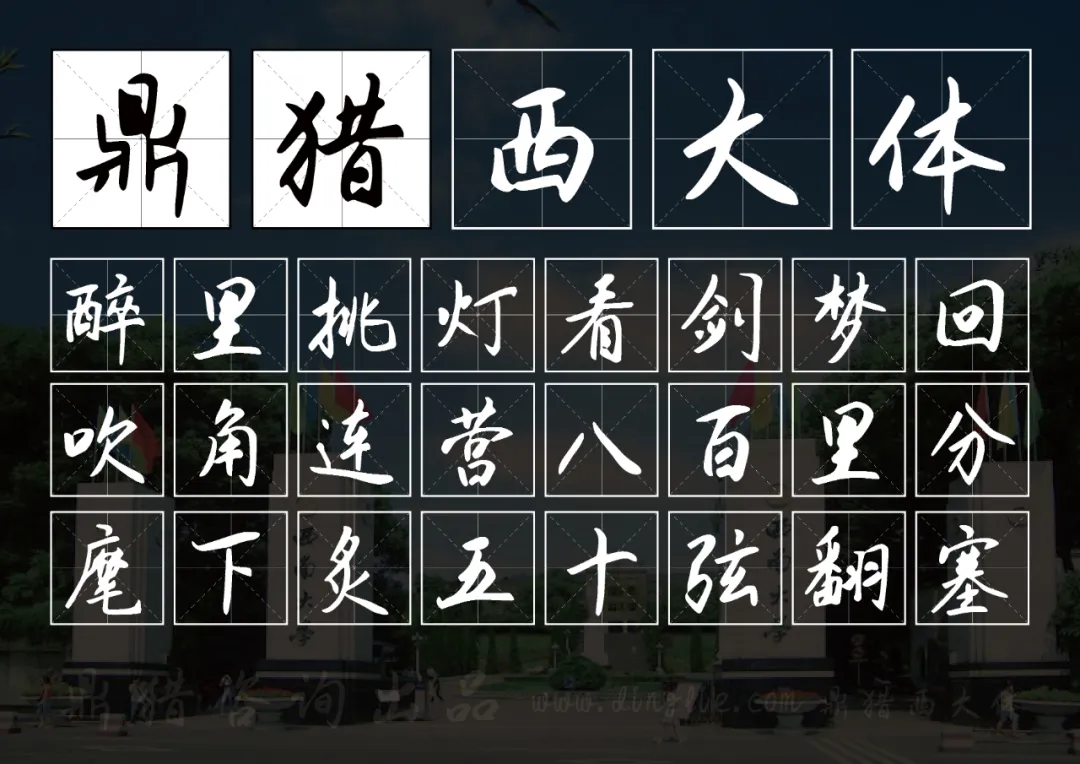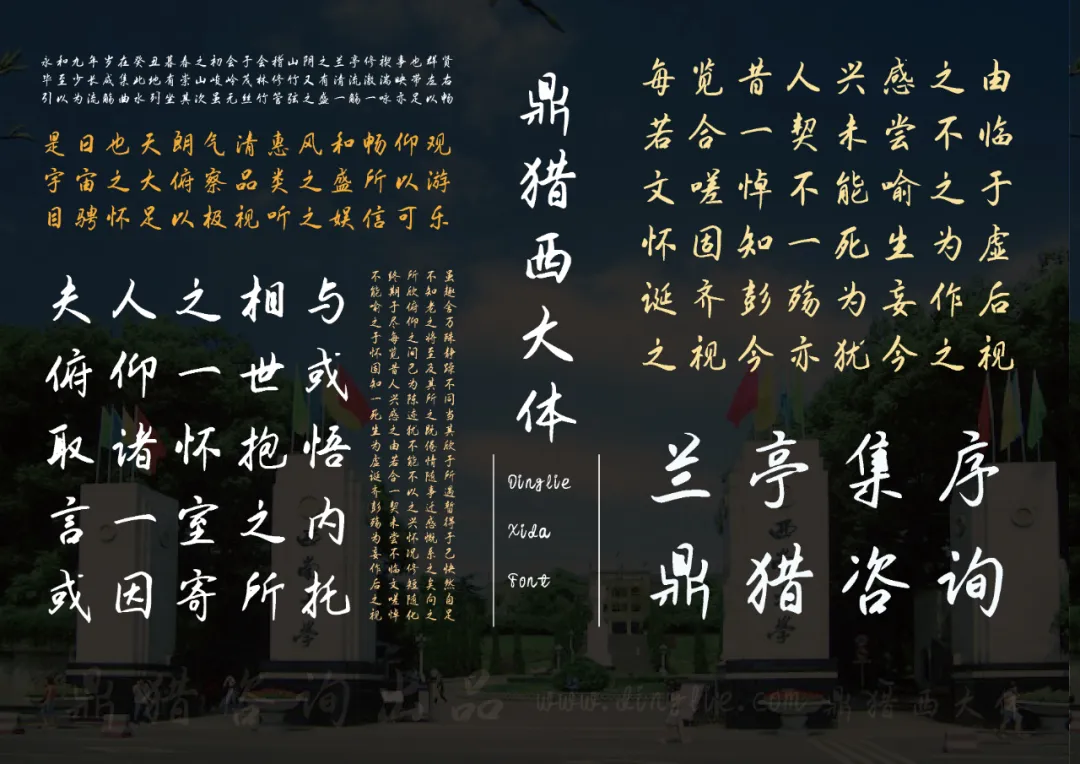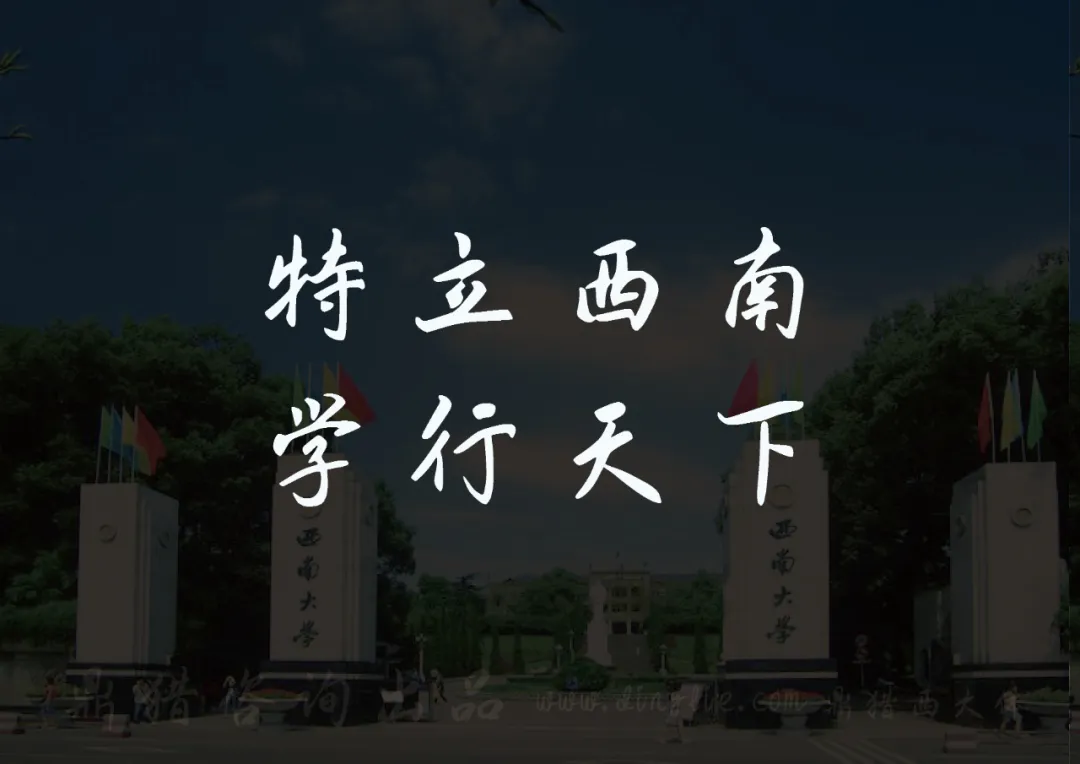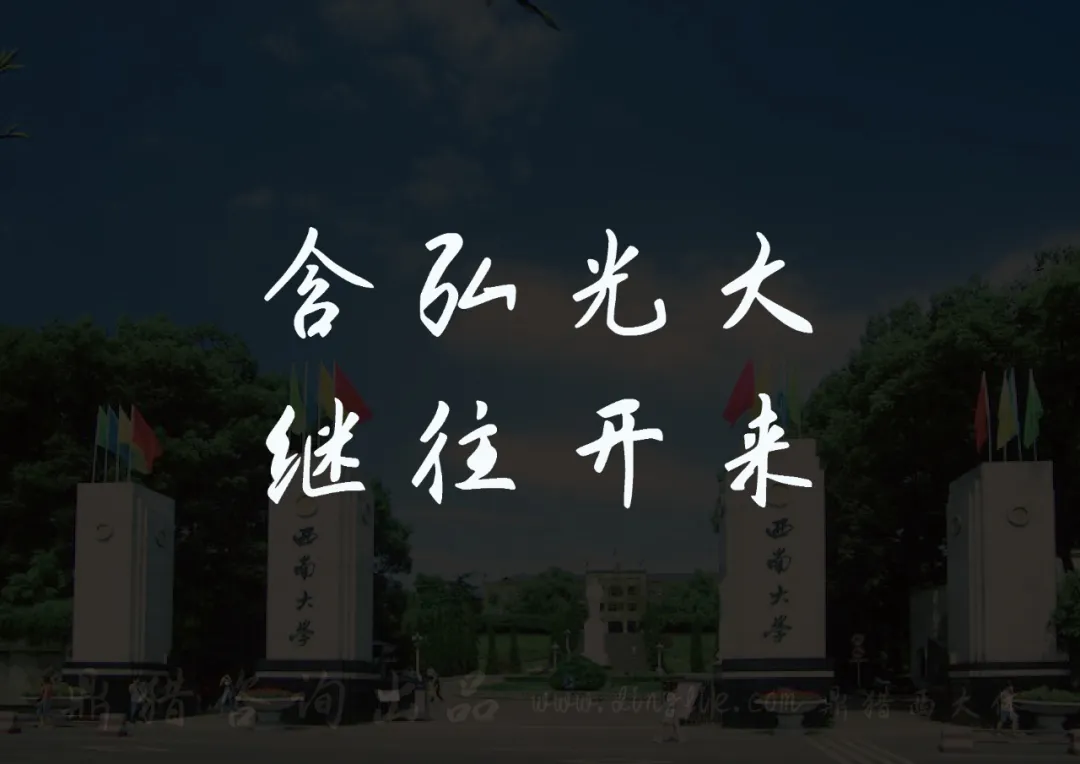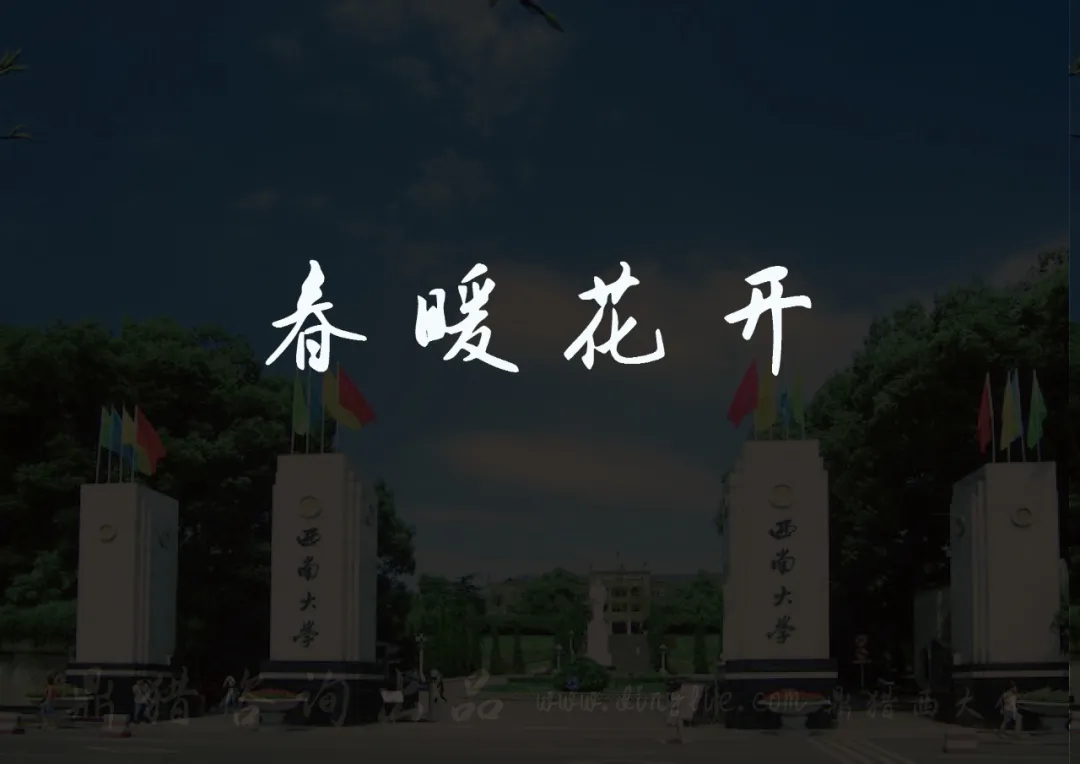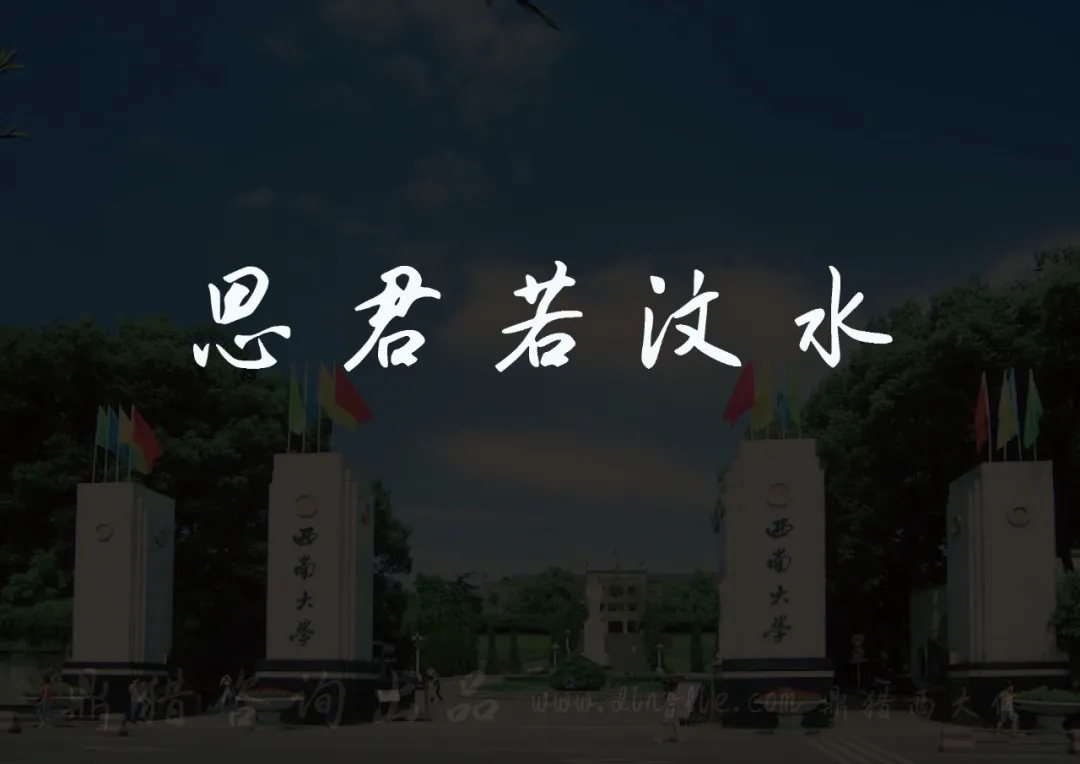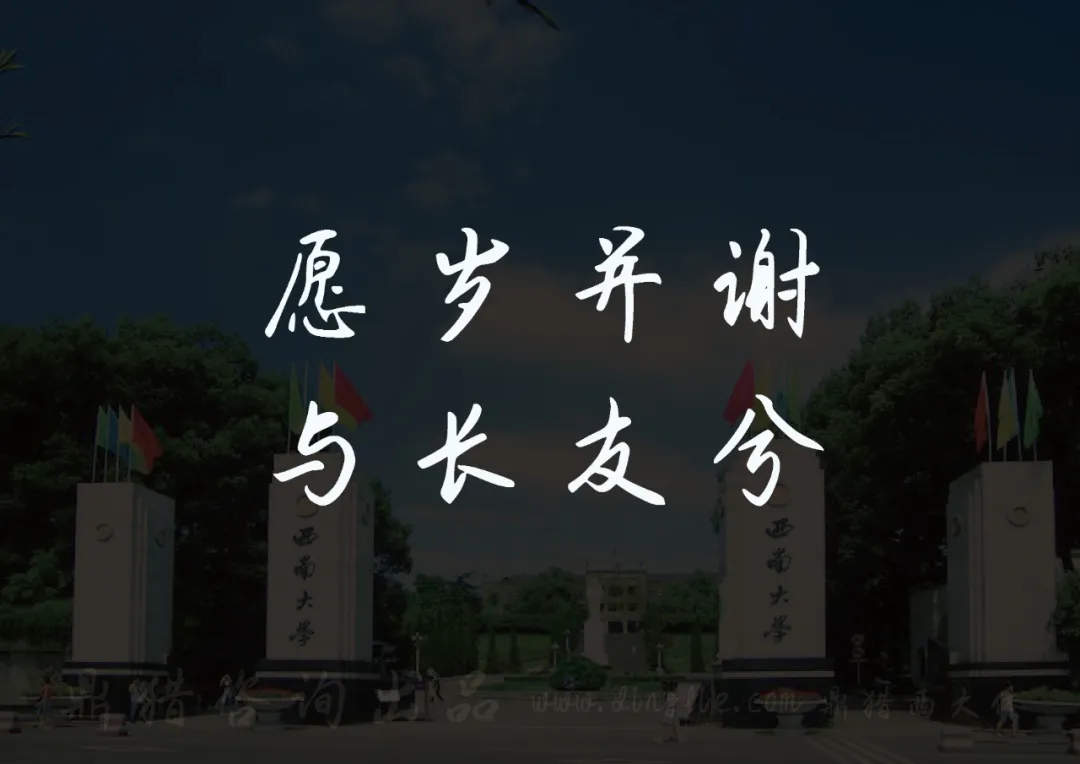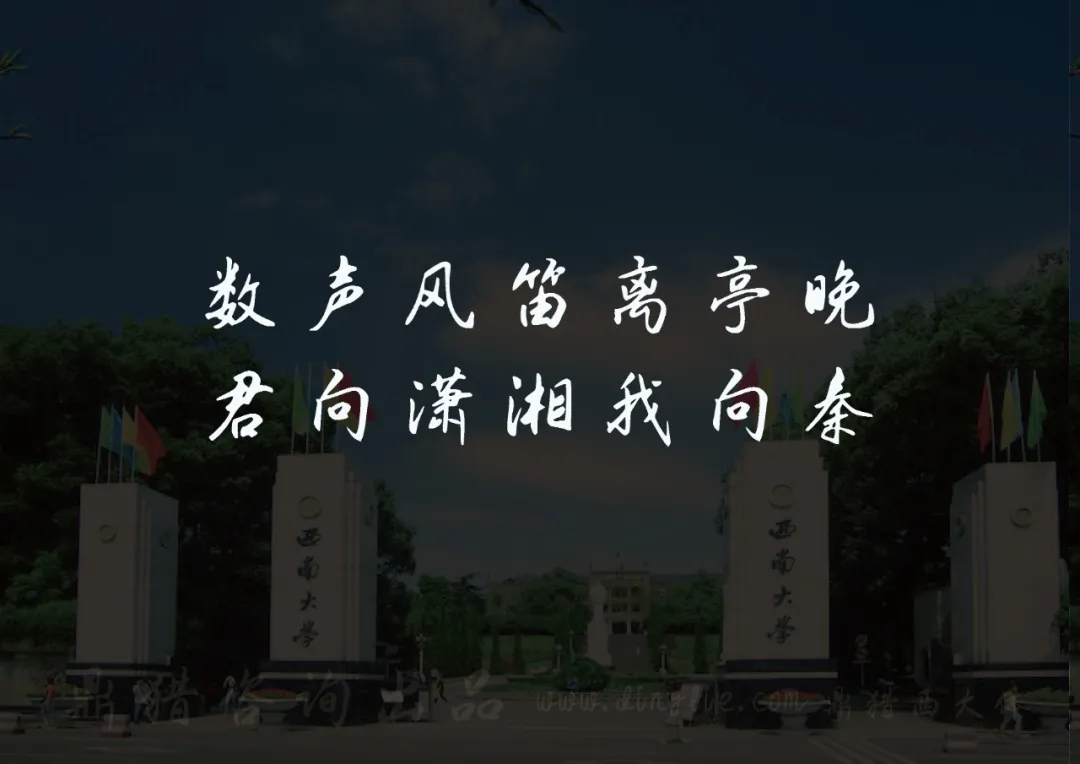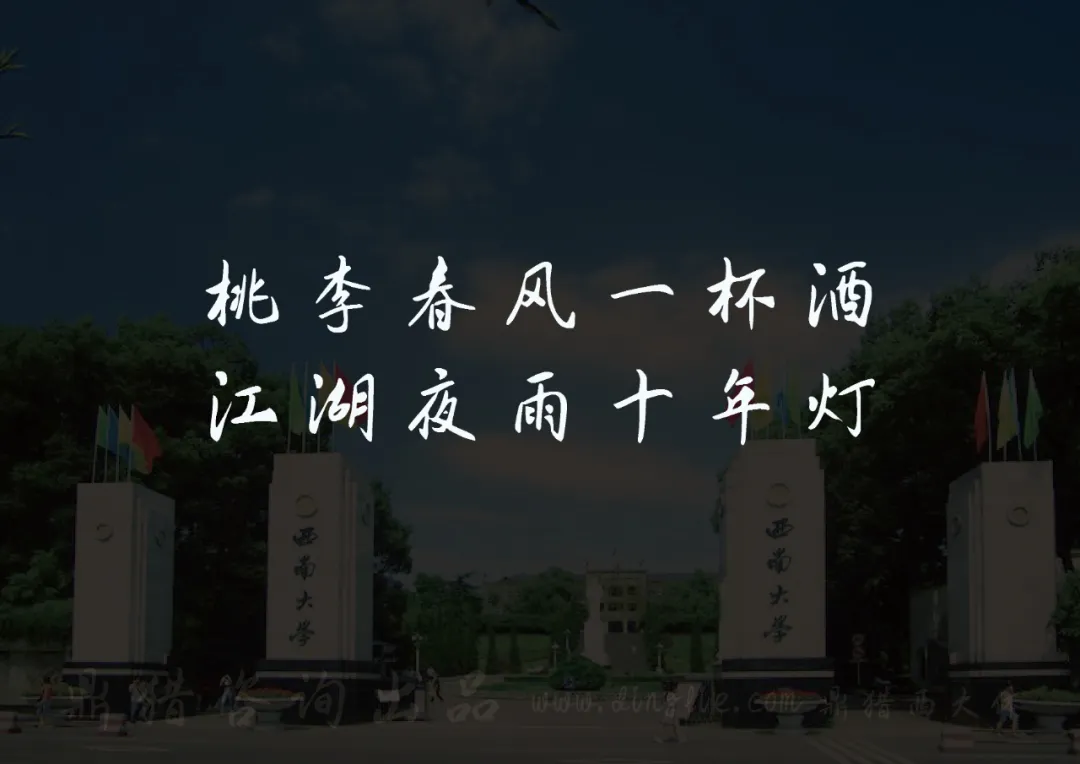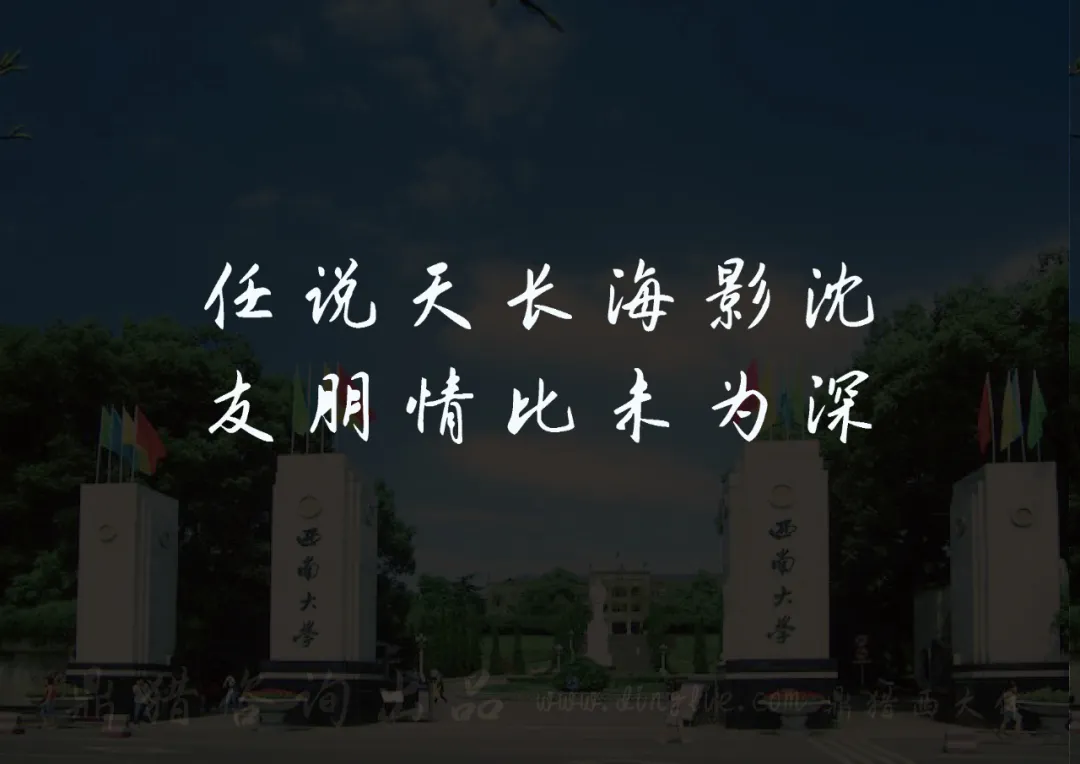
鼎猎西大体,
是一款自由的手写行楷。鼎猎西大体以作者母校简称命名,追忆恰同学少年。鼎猎西大体并不完美,就像是我们总有些遗憾的青葱校园岁月,也像我们总有些力所不逮的烟火生活。可,岁月悠悠,学海茫茫,人海茫茫。我们依旧载满美好的回忆与憧憬。鼎猎西大体排版时自由肆意,版式洒脱无拘,适合美食餐饮、文化艺术展览、企业文化,以及封面杂志海报、餐饮茶饮、美妆护肤等各个行业。